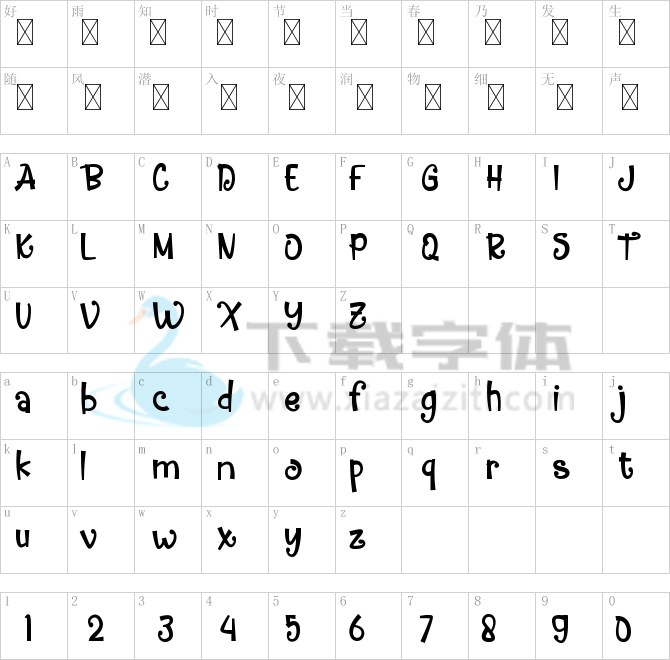
Accio Dollaro.ttf字体下载
Accio Dollaro.ttf字体下载,这款字体结构工整、笔画清晰,兼顾美观与易读性,适用于标题、正文、海报、包装、LOGO 等多种场景。字形优雅稳定,风格百搭耐看,适配日常排版与创意设计,让文字呈现更舒适、更具质感。Accio Dollaro.ttf字体下载一笔一画,皆是细节,以均衡的比例、流畅的线条打造舒适视觉体验,字形端正大气,风格简约现代。无论是商业设计、品牌宣传还是日常排版,都能轻松驾驭,让文字更有格调与力量。Accio Dollaro.ttf字体下载字体下载。